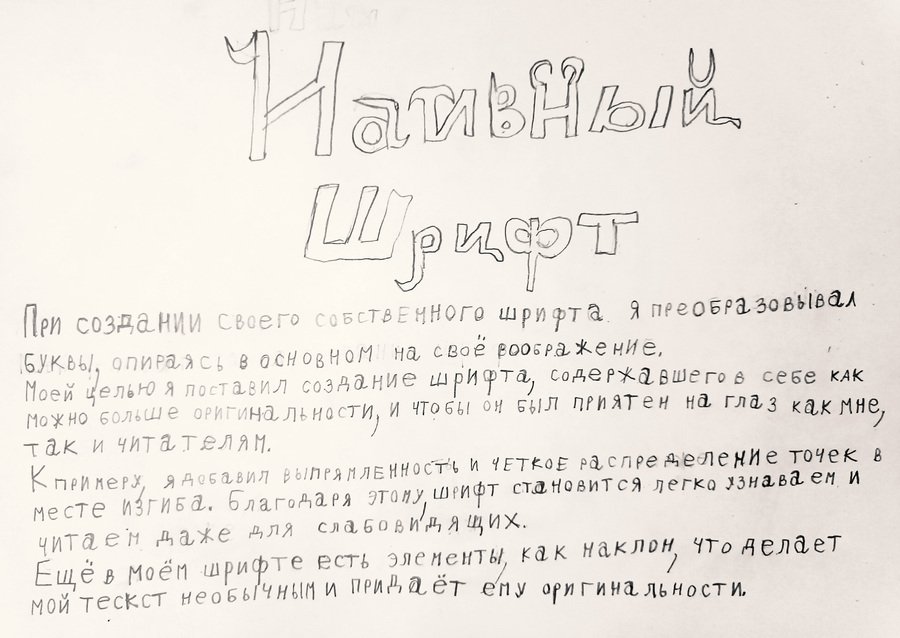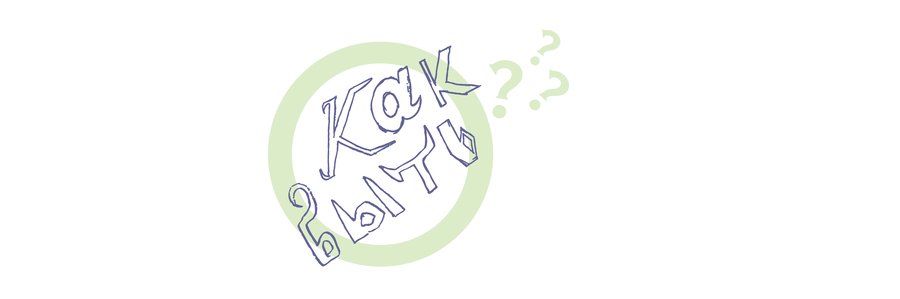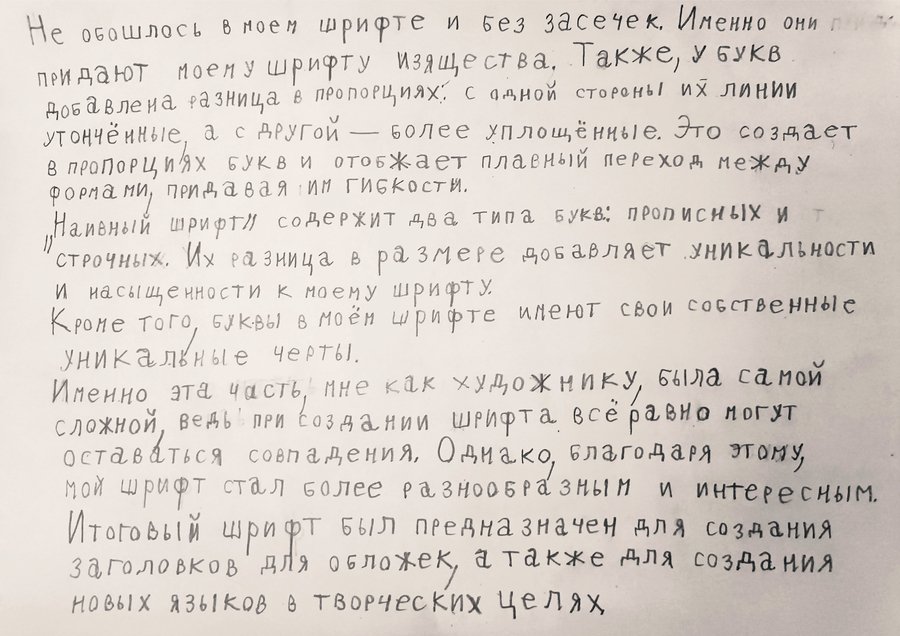
Наивный шрифт, и любовь к ближнему
Студент N попал к нам на курс случайно, видимо по ошибке. Наш курс называется „Проектирование шрифта“. Спустя пару недель стало понятно, что студент совершенно не приспособлен к проектной работе, потому что его modus cogitandi устроен весьма своеобразно.
Как только это выяснилось, мы порекомендовали ему перевестись туда, где художест­венная состав­ляю­щая первая в списке. К сожалению, свободных мест в таких группах не оказалось, и нам пришлось студента оставить на курсе шрифта.
Чтобы вы понимали масштаб проблемы: студент приходил почти на каждое занятие, но из всех брифов программы, он смог решить ноль заданий. — Ноль, Карл.
Мы решили дать возможность особенному студенту нарисовать особенные шрифтовые знаки так, как он их видит и чувствует. При этом всю проектную работу и техническую реализацию нам пришлось взять на себя.
Студенту было предложено выполнить
единственное задание, с которым
он мог справиться:
Прелюдия
Все наброски N делал исключительно линейными. Добиться того, чтобы формы были закрашенными, не получилось.
Один из первых листов, студент еще старается следить за пропорциями (слева вверху, подсказка преподавателя)
Переодически фантазия студента иссякала и он скатывался к однотипным, скучным формам, или же его уносило не в ту степь.
Когда такое случалось, мы показывали возможные конструкции и предлагали рисовать на их основе. Так, например, появились эти формы:
Весь процесс создания приемлемых набросков для наивного шрифта был по сути выяснением того, что еще из простого и обыкно­вен­ного не может сделать наш особенный студент.
Вместо тонких и аккуратных ограни­чи­вающих линий, студент умудрялся чертить кривые линии той же толщины, что и в буквах.
Ограничивающие линии прямо влияли на форму. Много­численные увеще­ва­ния, так не делать, результатов не возымели.
Я заверстал бланки с разлиновкой, но студент не нашел возможности их распечатать. Я предлагал сканировать листы с набросками, студент сказал, что доступа к сканеру у него нет. Единственное что оставалось, это фото на телефон.
Фрагменты необработанных фотографий в размере 100% слева, исходник, сделанный студентом справа, преподавателем
Пример экстремального качества. Как в принципе можно так фотографировать?
Фрагменты необработанных фотографий в размере 100% сверху, один из первых снимков этого листа снизу, последний «лучший»
Очередной рабочий лист. То, что попало в зону засветки, технически обработать невозможно.
Фото, сделанное студентом
Листы, которые N успевал набросать во время занятий, я снимал в классе. Листы выполненные дома, N снимал самостоятельно.
Получилось, примерно, половина снимков низкого качества, половина, обычного.
Дивертисмент
Все исходные буквенные формы были отобраны и творчески препарированы в шрифтовые знаки, из более чем восьми сотен авторских набросков.